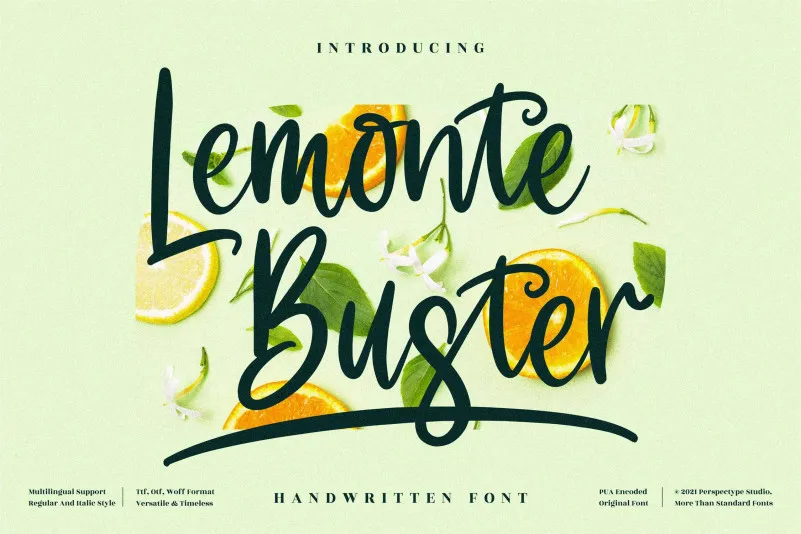
Lemonte Buster Font – Download Grátis
Aqui está uma versão em português do Brasil dos dois parágrafos solicitados para a descrição da fonte ‘Lemonte Buster’: Esta é uma fonte script leve e descompromissada, caracterizada por um estilo encantador que vai se adaptar com elegância a qualquer projeto. Independentemente do tema escolhido, Lemonte Buster se tornará uma peça indispensável em seu acervo de fontes, pois possui o potencial para transformar qualquer criação num verdadeiro espetáculo visual. Ideal tanto para textos como para gráficos, Lemonte Buster é perfeito para quem busca uma fonte que possa ser usada com versatilidade e sofisticação. Seja para adicionar um toque de personalidade a suas postagens no blog ou transformar seus projetos de design em obras de arte, esta fonte tem o poder de fazer sua marca mais impactante e atraente.